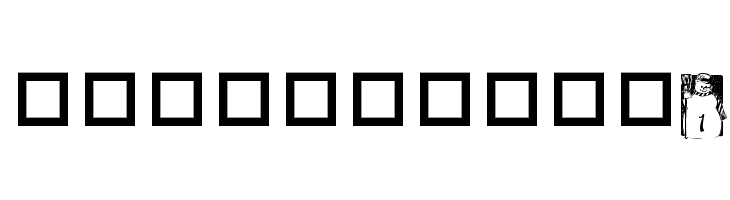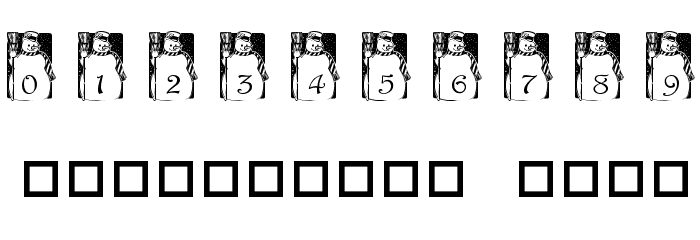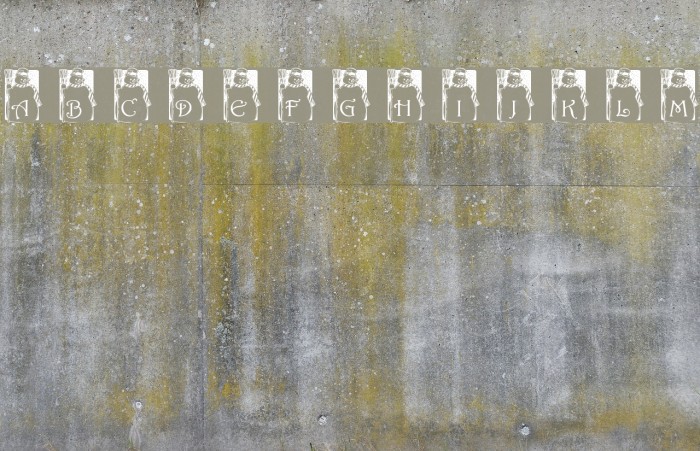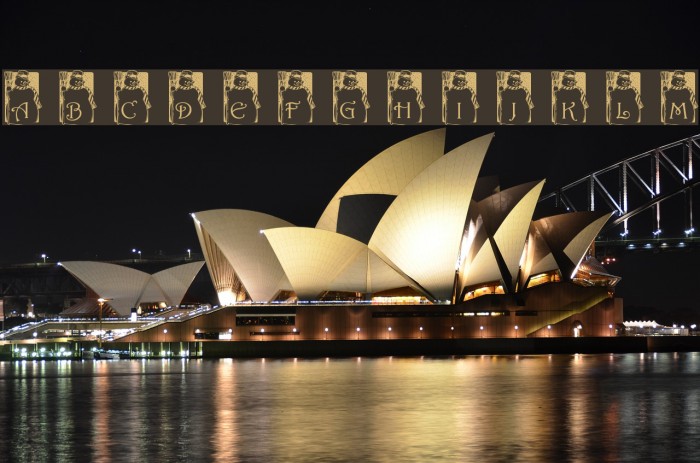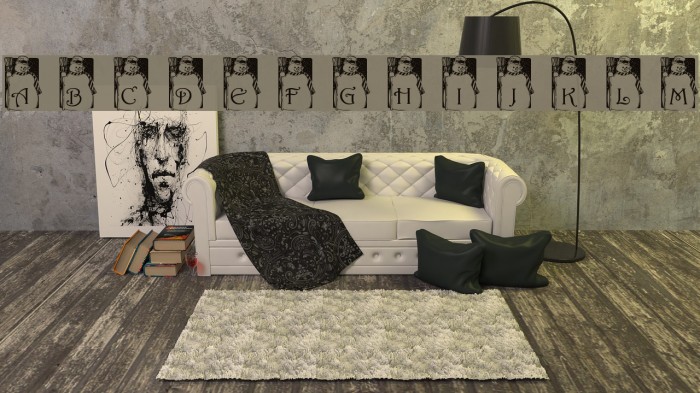
pf_snowman1 Font
Acest font include 40 caractere. Clic pe orice caracter pentru detalii.
| Proiecte propuse | Holiday cards, festive invitations, winter-themed posters, children's books. |